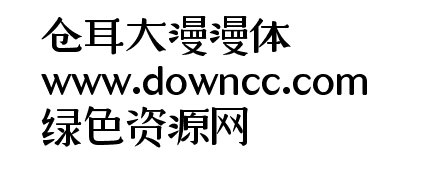
倉耳大漫漫體字體
倉耳大漫漫體是繼倉耳小漫漫體后推出的手寫字體,構(gòu)造上與倉耳小漫漫體非常接近,但整體結(jié)構(gòu)比較松散,字形交大,給文字更加清晰顯眼的呈現(xiàn),綠色資源網(wǎng)今日推薦!
倉耳大漫漫體字體特色
這款字體是一款追求個(gè)性的字體,在字體結(jié)構(gòu)上做出大膽調(diào)整,筆畫角度多變,擺脫正文字體的束縛,更加追求個(gè)性張揚(yáng),字體風(fēng)格略顯拙氣又帶有一些可愛。
倉耳大漫漫體W05
倉耳大漫漫體字體是一款適合漫畫行業(yè)設(shè)計(jì)的字體,整體纖細(xì)綿長,筆畫端正有力,造型上并未采用常見的結(jié)構(gòu)比例,隨意中更顯活潑,可以運(yùn)用在漫畫創(chuàng)作、創(chuàng)意海報(bào)設(shè)計(jì)等領(lǐng)域當(dāng)中。